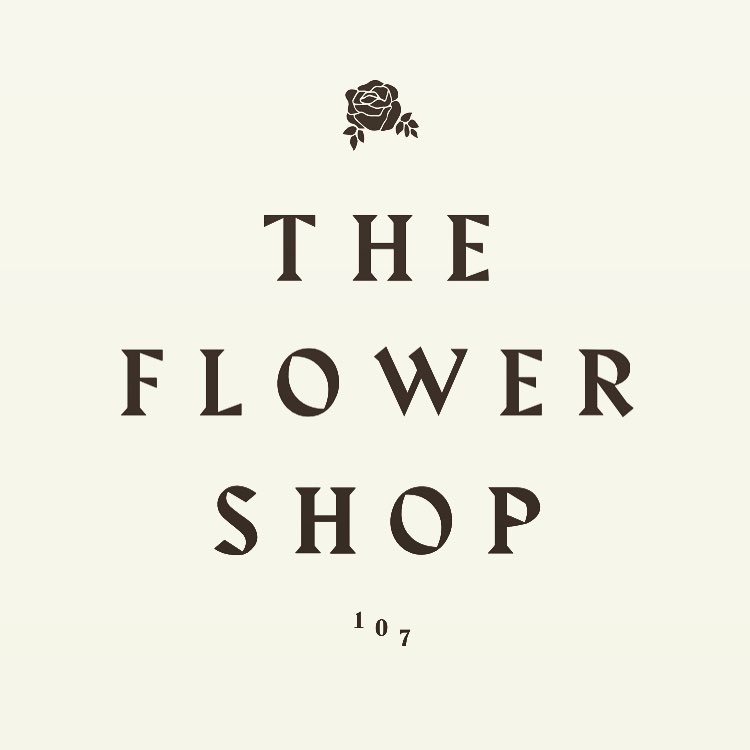
The Flower shop
NYCのレストラン&バー。70年代のおばあちゃん家のハウスパーティーみたいなくつろいだレトロな空間が今時のクールなんだとは、都会人の遊び心はひねりの効いてて面白い。店のサインに使われているフォントは、Harbour。70年代のクラブハウスのサインのようなイメージもありつつ、ルーズなレタースペースで現代的なクールさも持たせている。
A restaurant and bar in New York City, where a laid-back retro space that looks like a house party at grandma's house in the 70s is the cool thing to do these days. The font used for the sign is Harbour, which has the look of a 70's clubhouse sign, but with a loose letter spacing that gives it a modern coolness.
Harbourはブラックレター風のディスプレイ用のセリフタイプフェイスです。Harbour はラテンとゲルマニックのスタイル-文化的に政治的にそして美的に対立する2つのレターフォーム–のぶつかりあいです。ラテンタイプフェイスのレターフォームは幾何学が基本ですがブラックレターはカリグラフィーが基本です。Harbourはペン由来のカリグラフィックな形を生かしつつタイプフェイス自体はペンで書かれた文字というよりも活字として明確に設計されたダイナミックなレターフォームとして制作されています。
Harbour is a clash of Latin and Germanic typestyles - two conflicting letterforms, culturally, politically and aesthetically. Latin letterforms have a geometric base, blackletter types are calligraphic. Harbour takes calligraphic forms that derive from writing with quills, but is a typeface that is clearly drawn‚ rather than written‚ to produce graphic, dynamic letterforms.